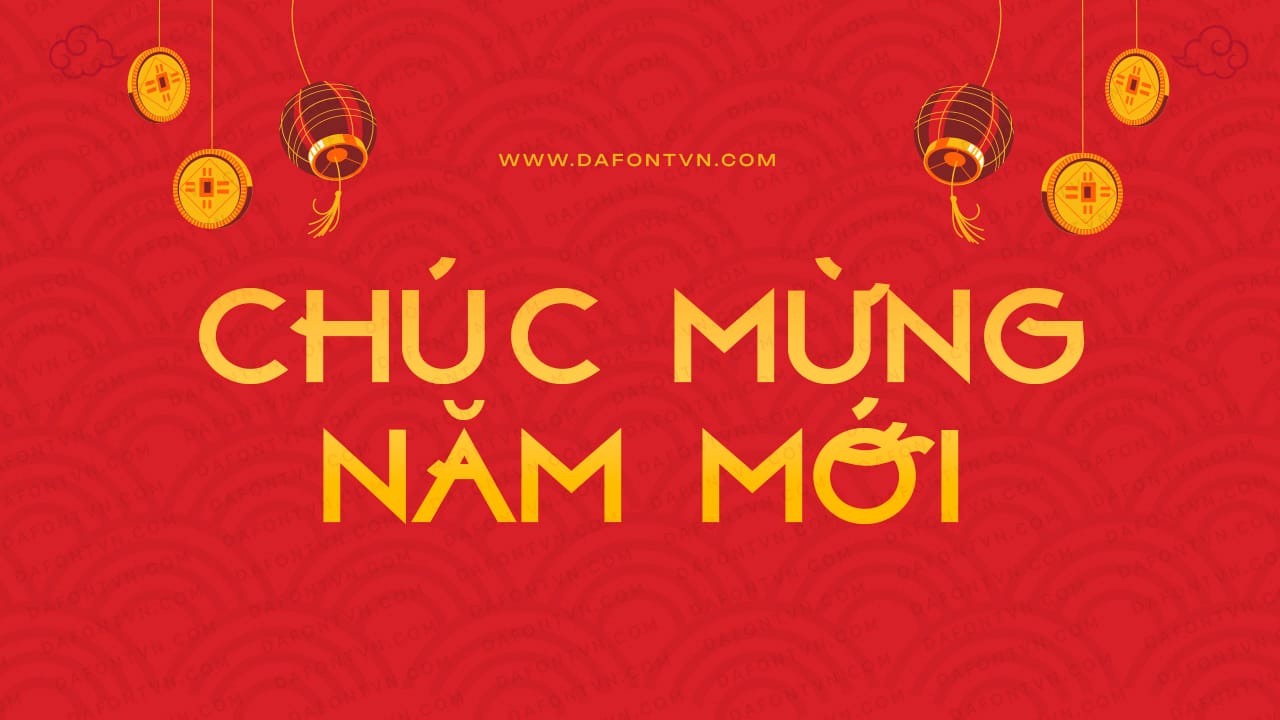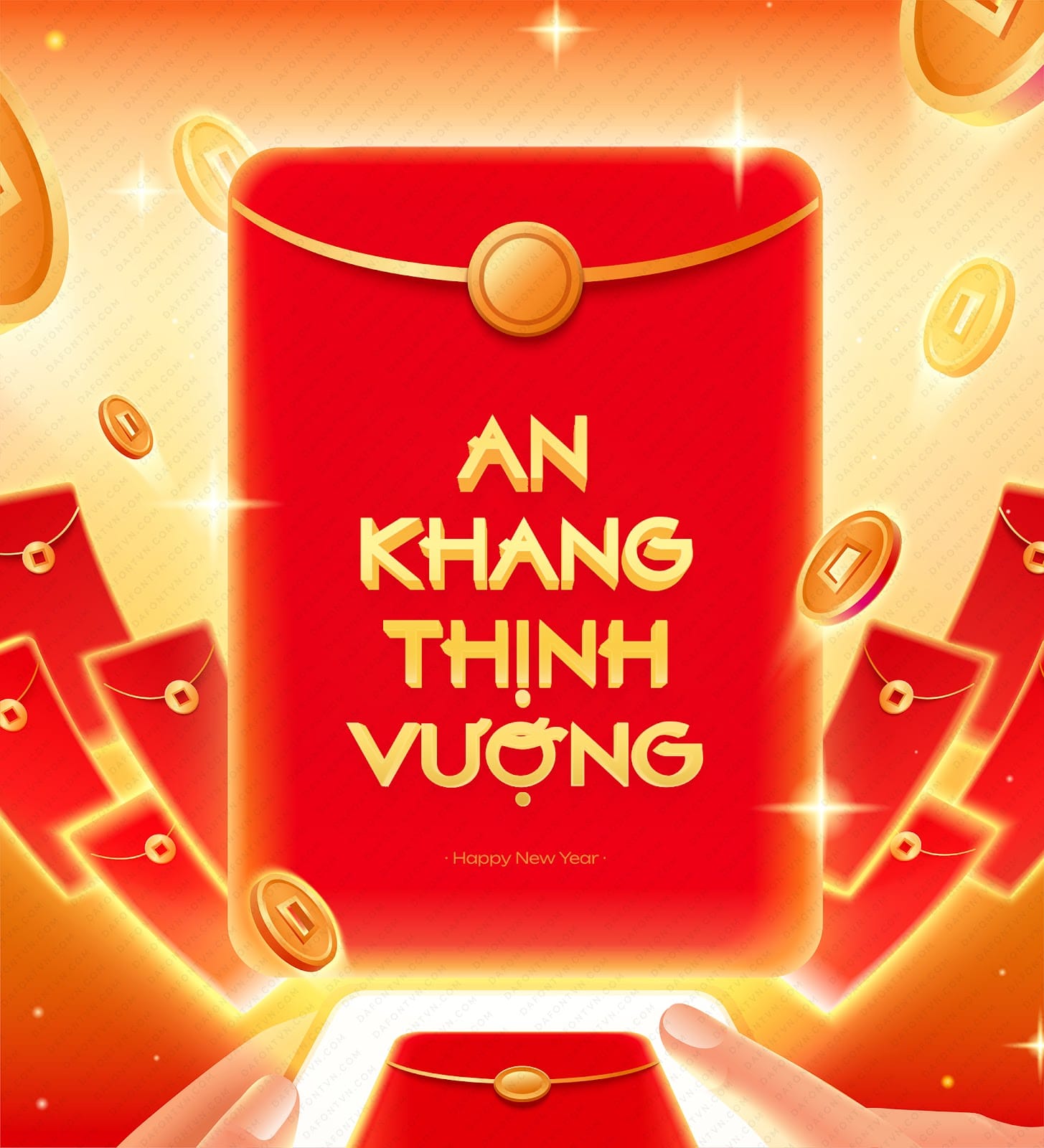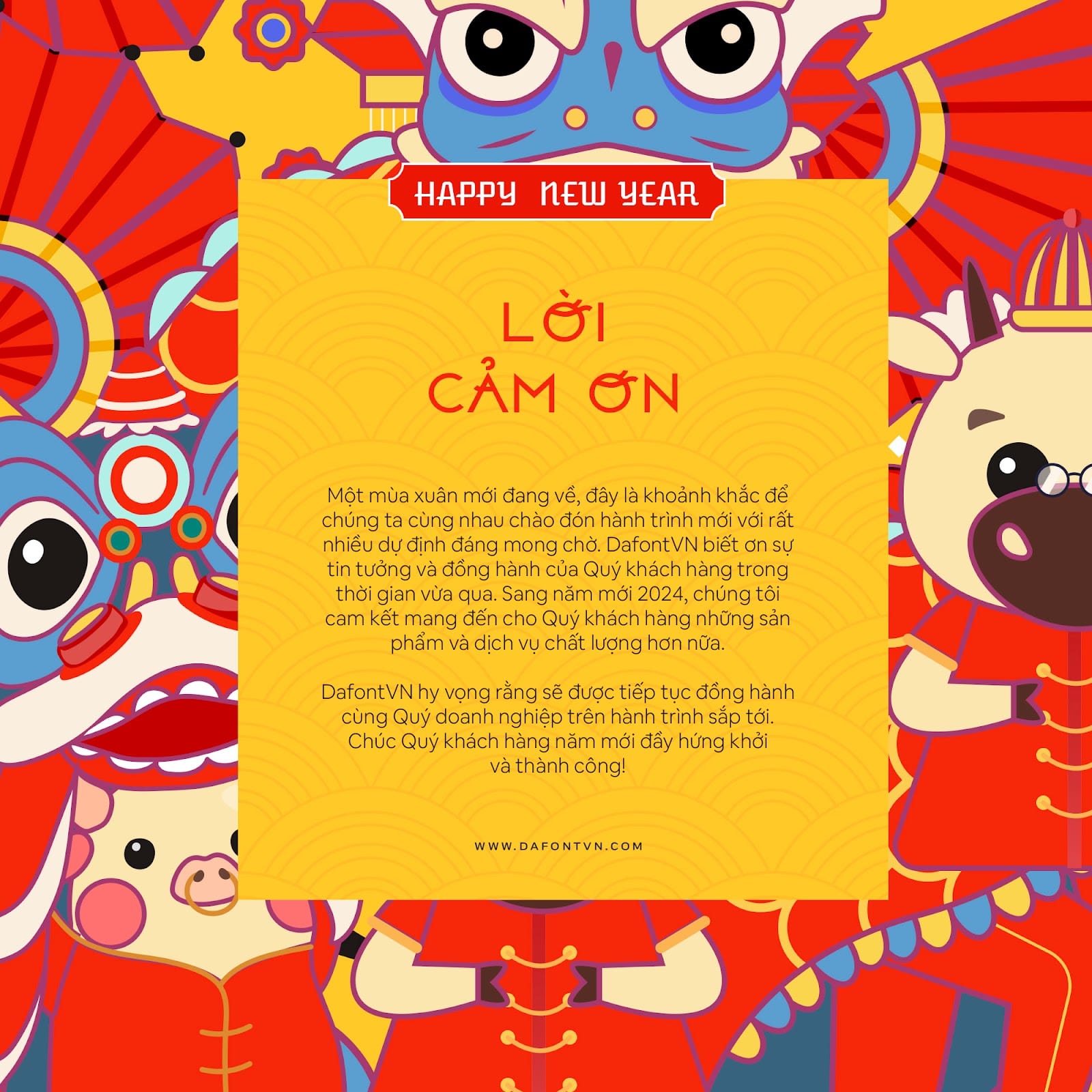
Font việt hóa TUV Above (4 font) – Font Tết
TUV Above bộ font bao gồm 4 kiểu Light – Regular – Bold – Black. Above là một font chữ được thiết kế với tất cả các ký tự in hoa, tuy nhiên 1 số ký tự được thiết kế khác nhau khi gõ ở chế độ thường và in hoa.Phông chữ sans serif này hoàn hảo để tạo ra các thiết kế sang trọng và tinh tế. Cho dù bạn đang thiết kế bố cục cho tạp chí thời trang, thiết kế logo mới, các dự án dịp lễ tết hay tạo lời mời hoặc trích dẫn, Above sẽ mang đến cho dự án của bạn vẻ sang trọng. Với những đường nét rõ ràng và sức hấp dẫn vượt thời gian, phông chữ này chắc chắn sẽ trở thành phông chữ được yêu thích!
Font việt hóa TUV Above preview 2
Font việt hóa TUV Above preview 3
Font việt hóa TUV Above preview 4